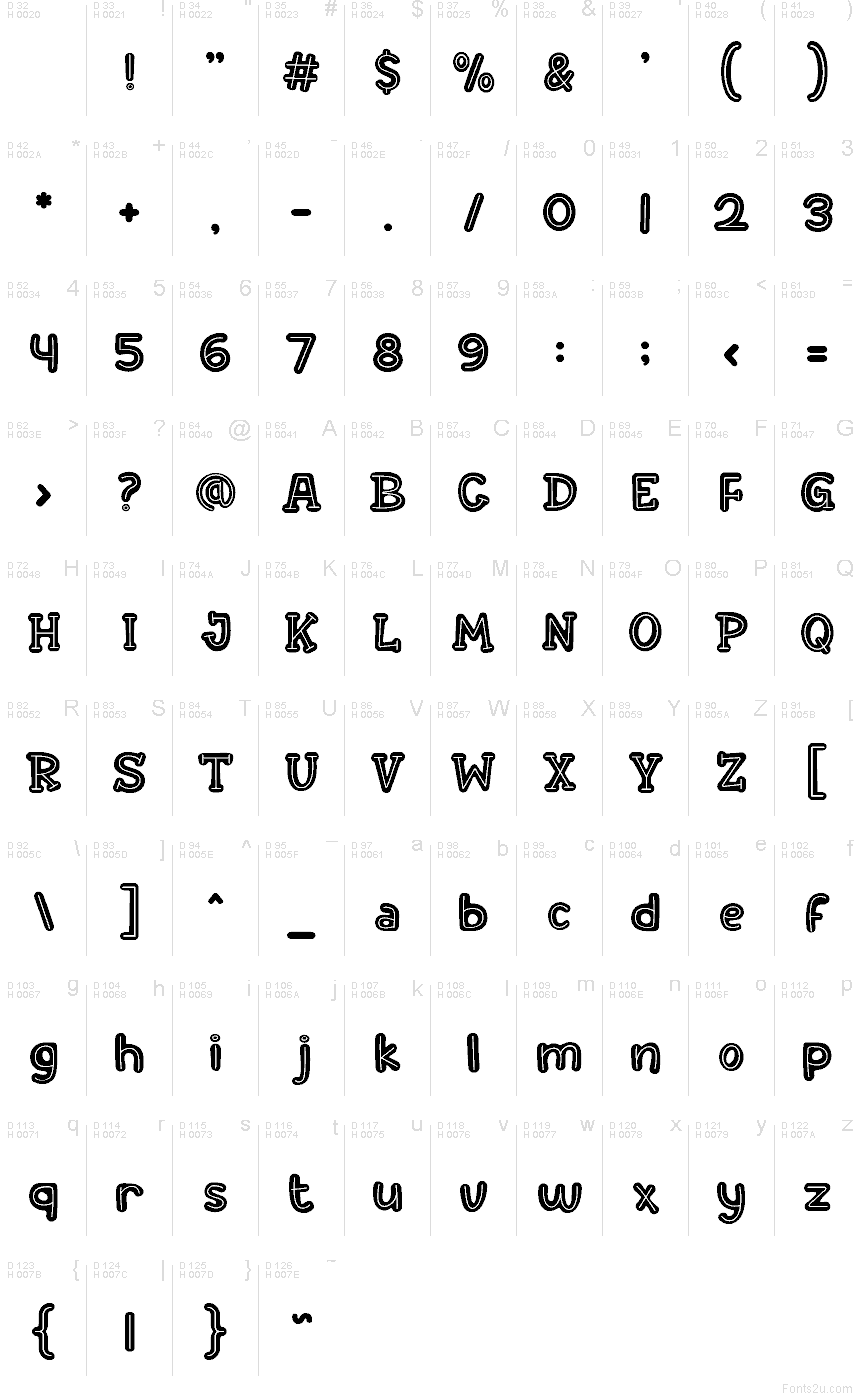
Crayon Craft One
Crayon Craft One od Putracetol Studio je bezplatné písmo typu display v štýle voskovky, definované hrubými zaoblenými obrysmi a druhou vnútornou kontúrou, vďaka ktorej pôsobí každé písmeno ako ručne kreslené. Táto dvojitá silueta dodáva písmenám mäkký a remeselný vzhľad namiesto strohého geometrického spracovania.
Skvelo sa hodí na školské plagáty, obálky detských kníh, pracovné listy, párty nápisy a ručne vyrábané obaly, kde obrysové formy evokujú vyfarbovanie, obtahovanie a papierové vystrihovačky. Najmä kratšie nadpisy ťažia z jeho živých kriviek, ktoré udržujú písmo priateľské a grafické bez toho, aby sa zmenilo na generický bublinový štýl.